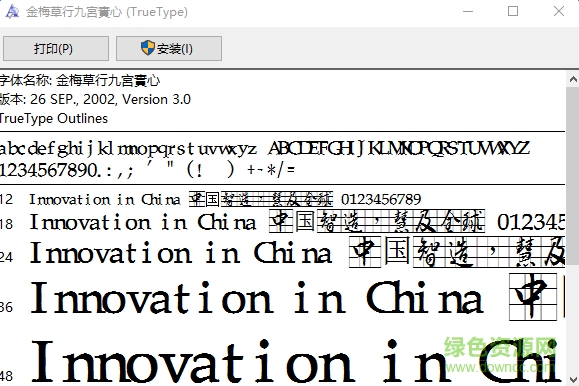
金梅草行九宮實(shí)心字體是金梅字庫中很有個性的一款實(shí)心字體,所謂實(shí)心字體就是寫出來的字整個都是實(shí)心的,而且這款字體活潑大方,字形很是好看,大家不妨來綠色資源網(wǎng)下載體驗(yàn)一番。
金梅草行九宮實(shí)心字體寫出來的字很好看而且是很耐看的那種,有自己的獨(dú)特的魅力之處,相信大家試過之后也會喜歡的,歡迎大家來綠色資源網(wǎng)下載。